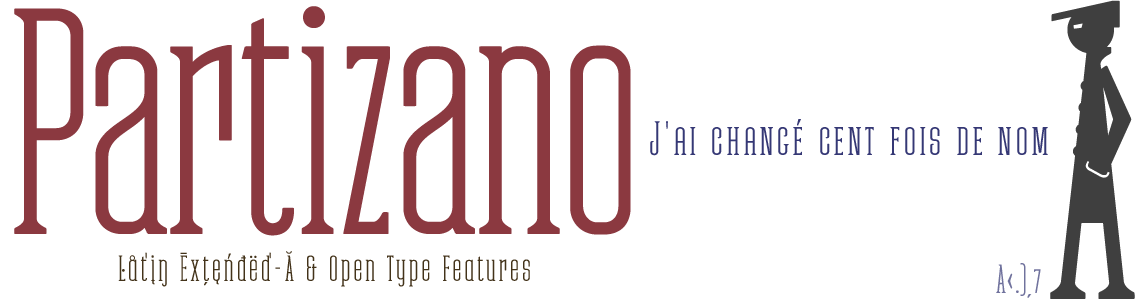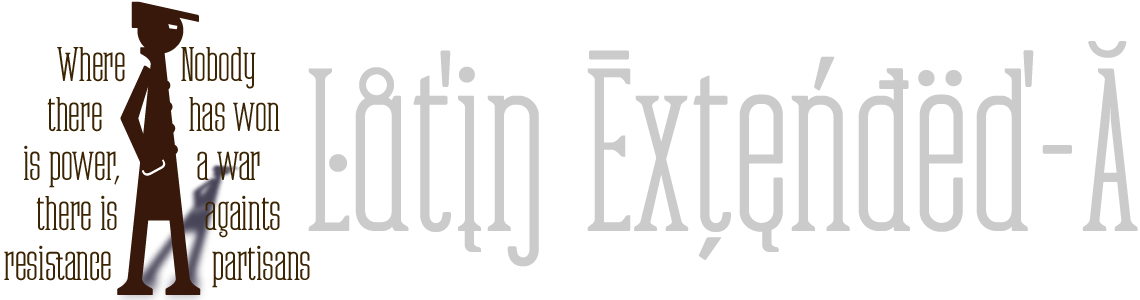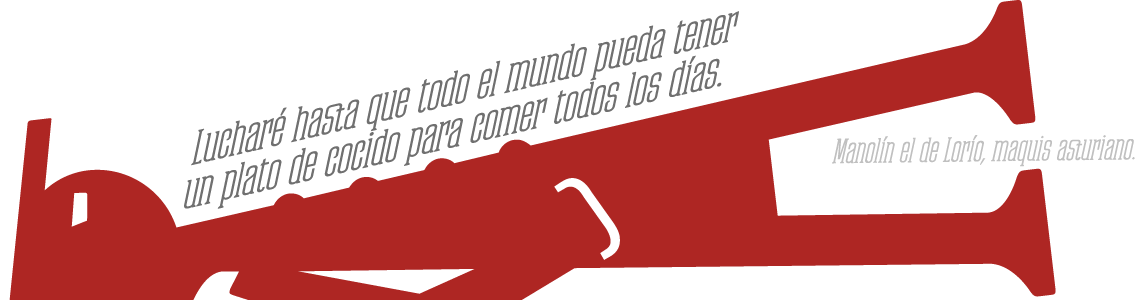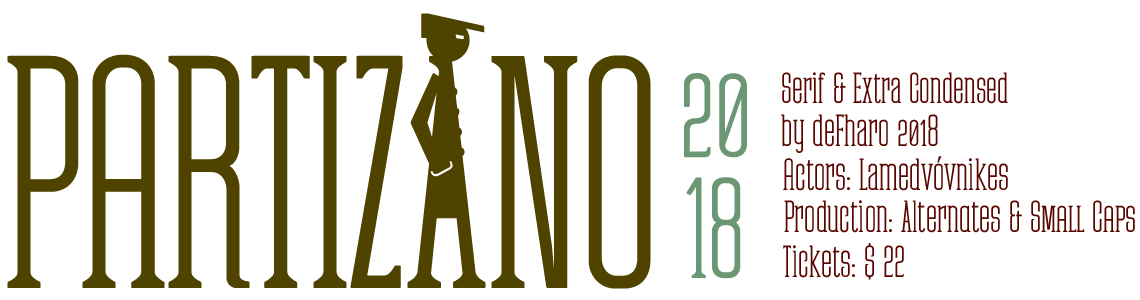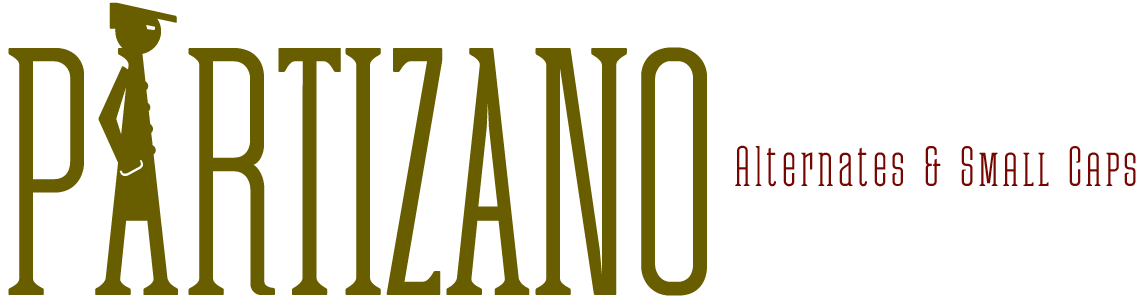
Usar las las siguientes teclas para escribir el símbolo del bitcoin y el icono del partisano:
b#, a#
Estilo: Serif, Display, Retro, Geometric
Proporción: Extra condensada, Regular & Versalitas
Glyphs: 685
Alternates: 63
Autor: deFharo
Año de publicación: 2017.
Funciones OpenType: Additional languages, All Alternates, Alternate Annotation Forms, Capital Spacing, Contextual Alternates, Denominators, Discretionary Ligatures, Extended Fractions, Historical Forms, Inferiors, Kerning, Localized Forms, Numbers Small Caps, Numerators, Oldstyle Figures, Ordinals, Scientific Inferiors, Slashed Zero, Small Capitals, Stacked Fractions, Standard Ligatures, Subscript, Superior letters, Superiors, Superscript.